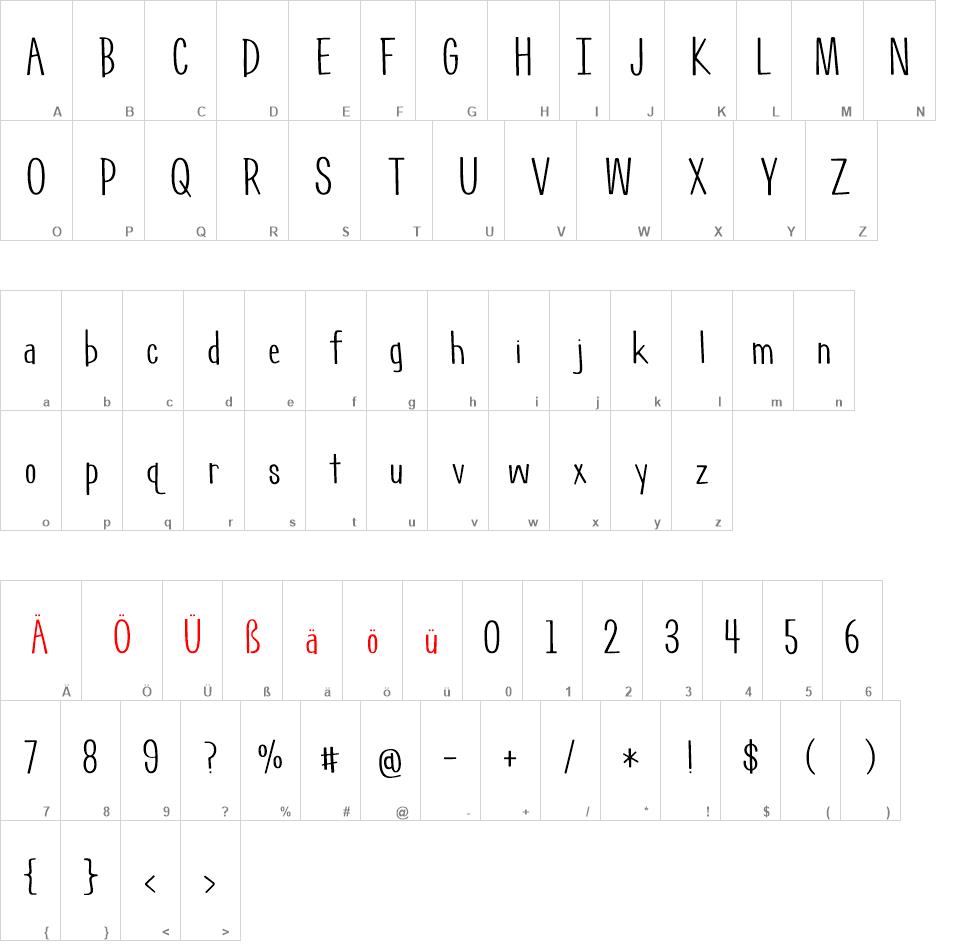
Geektastic
Geektastic font
Geektastic
Geektastic ist eine große und schlaksige, hinreißend introvertierte Hand-Sans in zwei Gewichten - normal und dünn. Es ist schrullig, aber unaufdringlich, und sogar kommt mit einer "Zusatzschriftart" mit fünf Charakteren - 3 Bowties und zwei Sätzen der Gläser.
Enthält 366 Zeichen mit vielen Buchstaben mit Akzenten.